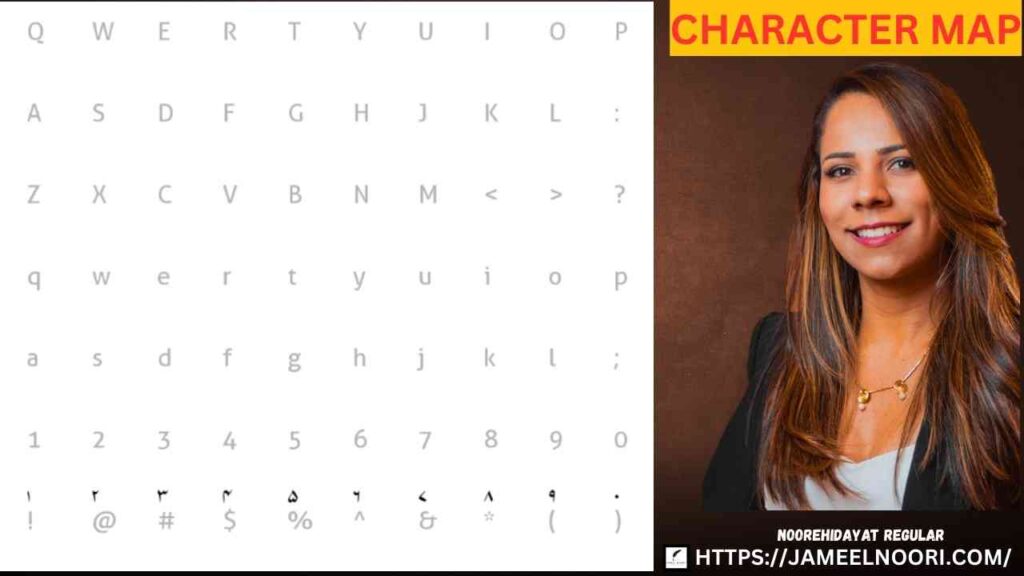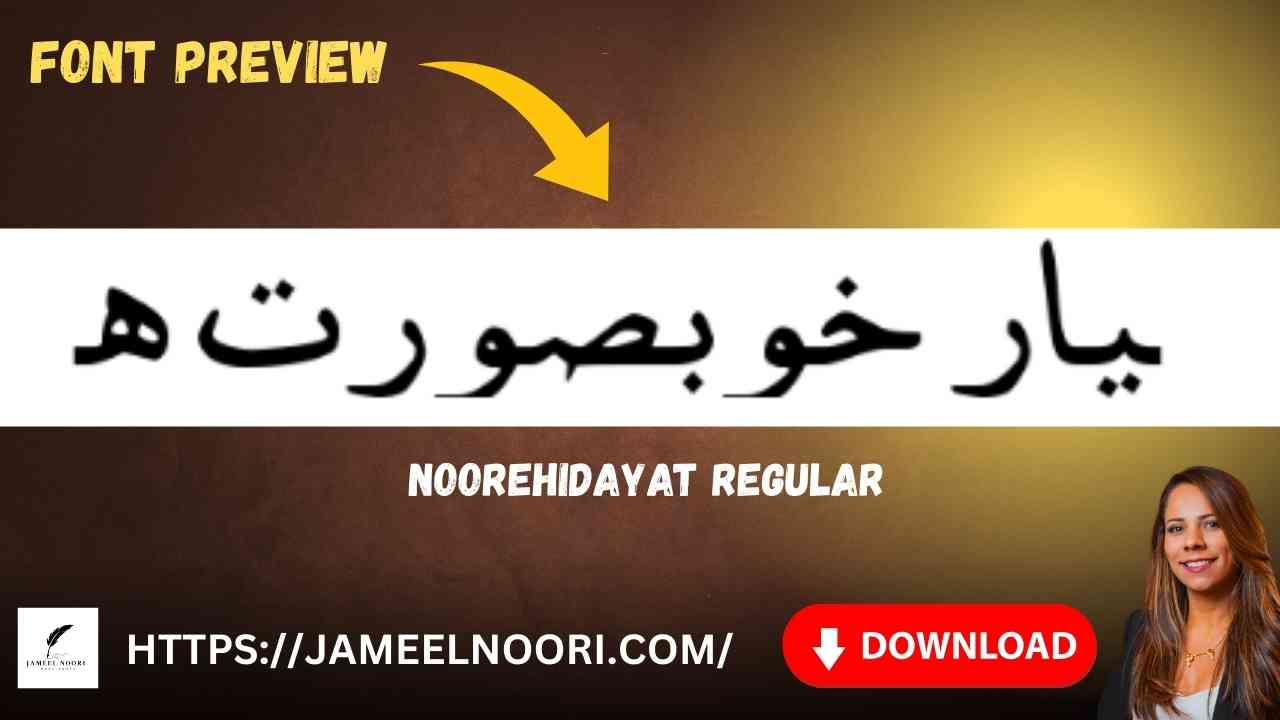
Download Urdu Font Noorehidayat Regular – Complete Guide
Introduction – Download Urdu Font Noorehidayat Regular
Agar aap Urdu fonts ke shaukeen hain to aap zaroor Download Urdu Font Noorehidayat Regular karna pasand karenge. Ye ek Regular TrueType Font hai jo Urdu typing aur designing ke liye bohot widely use hota hai. Iska simple aur elegant style Urdu scripts ko ek professional aur eye-catching look deta hai, jo students aur designers dono ke liye ideal hai.
Features of Download Urdu Font Noorehidayat Regular
Jab aap Download Urdu Font Noorehidayat Regular karte hain, to aapko kai khaas features milte hain jo is font ko unique banate hain:
• ✅ Smooth aur clear Urdu typing ke liye design
Why Choose Download Urdu Font Noorehidayat Regular?
Bahut se log sochte hain ke Urdu ke liye best font kaunsa hai. Agar aap readability aur professional writing chahte hain to Download Urdu Font Noorehidayat Regular best choice hai.
• Ye newspapers, magazines, aur books me use hota hai.
• Designers aur publishers isay prefer karte hain.
• Simple aur clean look provide karta hai.
Agar aap Urdu typing aur designing ko professional touch dena chahte hain to Download Urdu Font Noorehidayat Regular aapke liye ek must-have choice hai. Ye font stylish, affordable aur easy-to-use hai jo har Urdu content writer, student aur graphic designer ke liye best option sabit hota hai. Thousands of users ki positive rating aur wide usage iski popularity ka saboot hai.